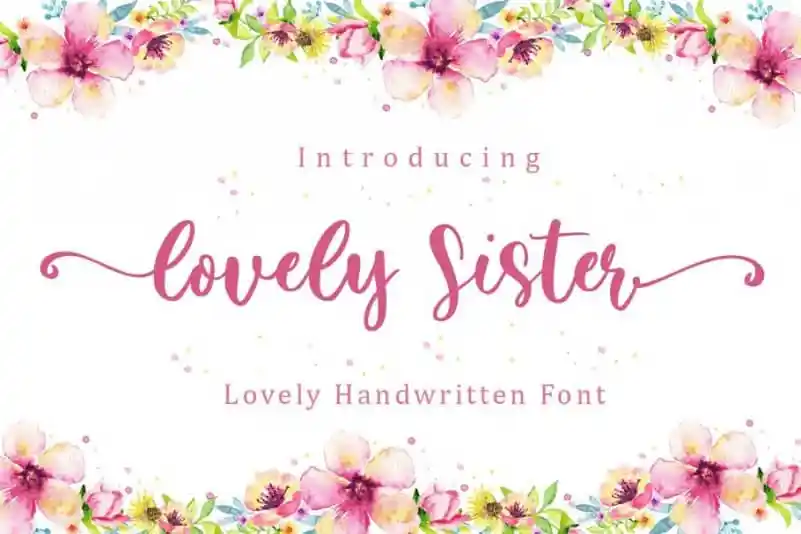
Lovely Sister Calligraphy Font – Download Grátis
A “Lovely Sister Calligraphy Font” é uma criação criativa que encanta os olhos com seu estilo de calligrafia artesanal e seus caracteres decorativos que se movem, como danças. Desenvolvida pelo talentoso font designer Sronstudio, esta font é perfeita para o design criativo. Ela é ideal para a decoração de eventos, desde os mais formais até as celebrações mais íntimas, permitindo um toque único em tudo – do cartão de convite à embalagem de produto, ou mesmo nas criações artísticas da sua galeria de fotos. Com uma base de linha que se move e um ar de diversão na forma dos caracteres, a “Lovely Sister Calligraphy Font” é perfeita para quem procura uma fonte de calligrafia que seja tanto estilosa quanto versátil. Seja você um designer gráfico, um artista ou simplesmente alguém que aprecia algo novo e elegante na sua próxima missão criativa, este font oferece uma maneira única de expressar a sua personalidade no design.